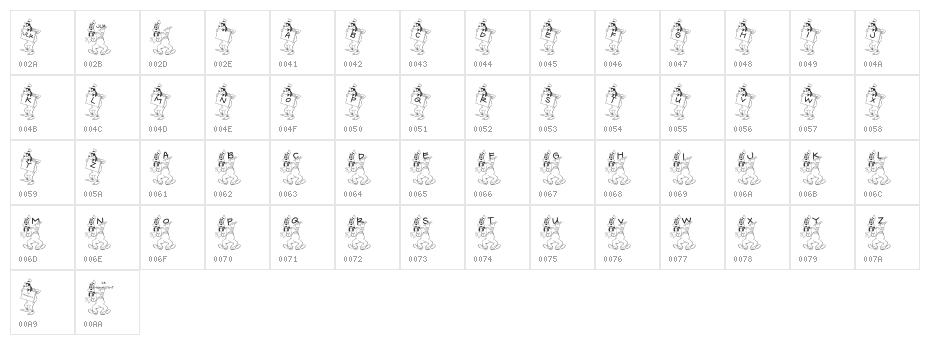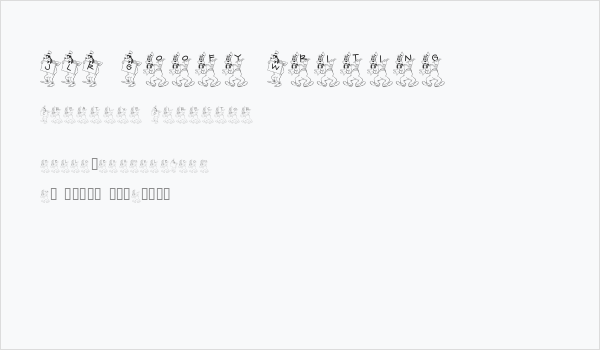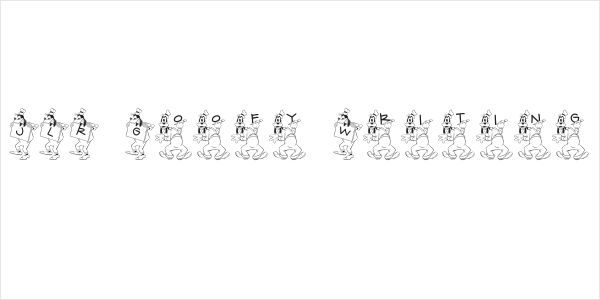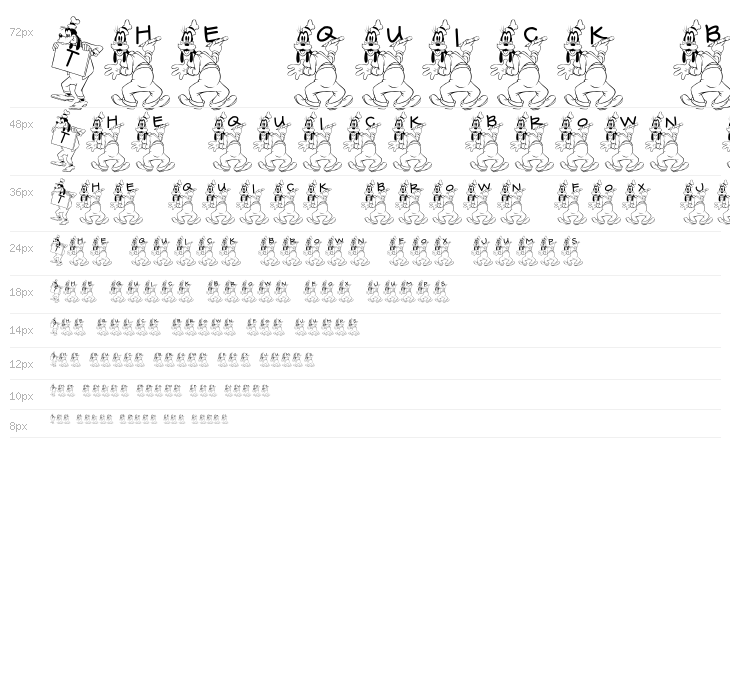
JLR Goofy Writing Font
| Stile generale | Whimsical, Fun |
| Caso d'uso | Logos, Posters, Invitations |
| Progetti proposti | Ideal for children's books, playful branding, party invitations, and themed event materials. |